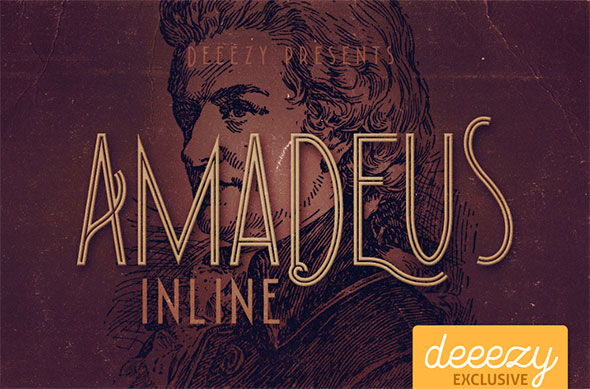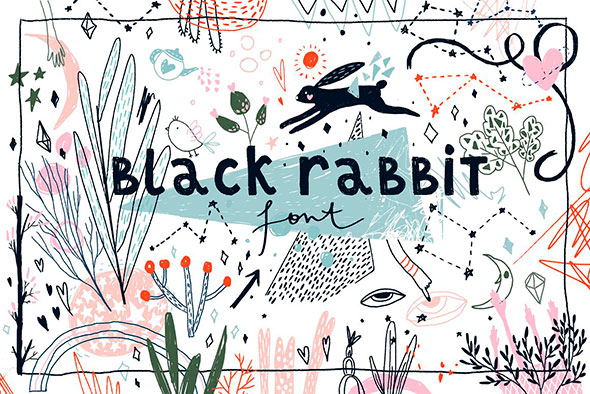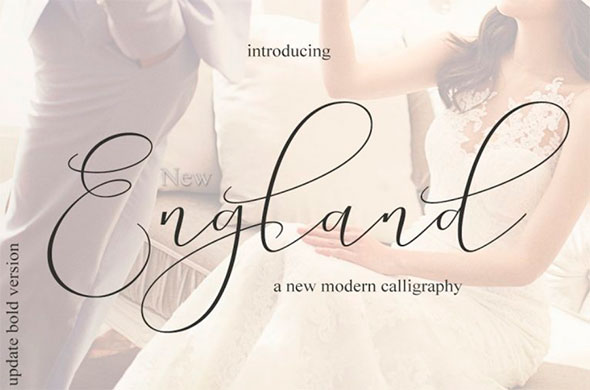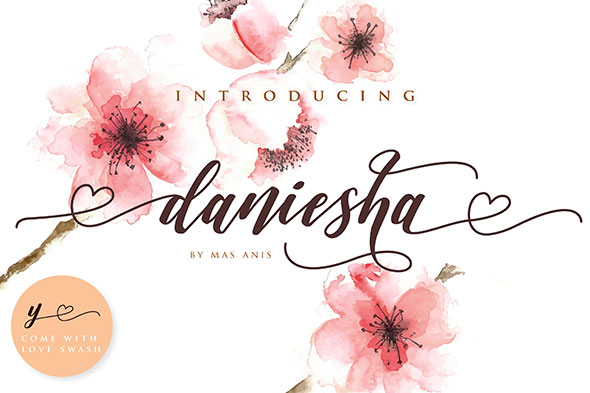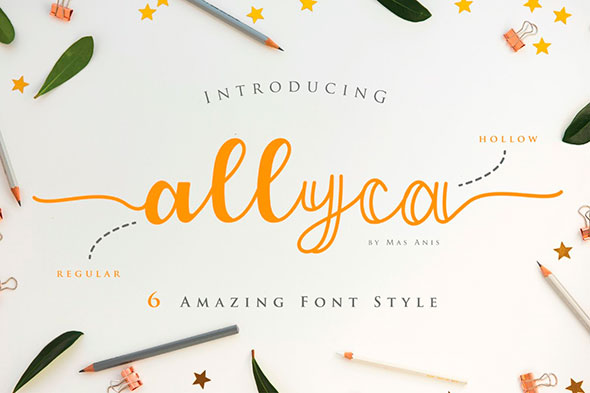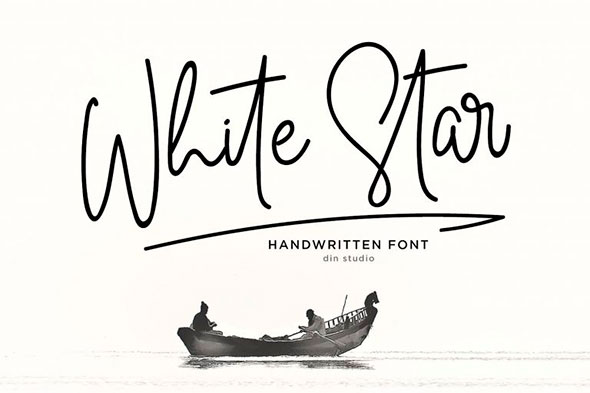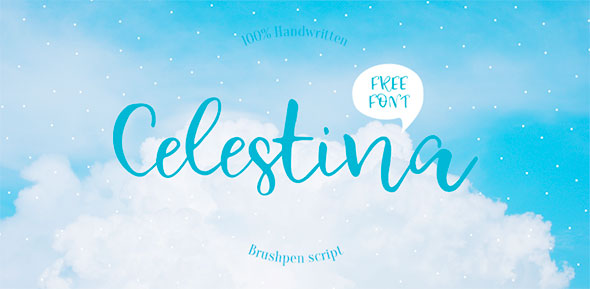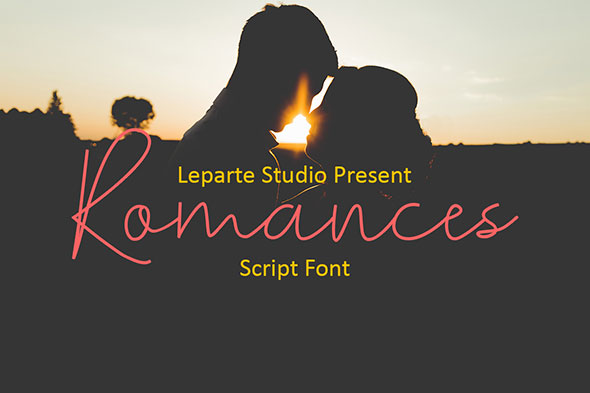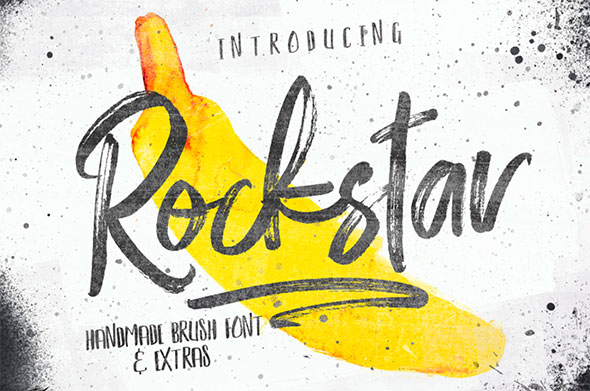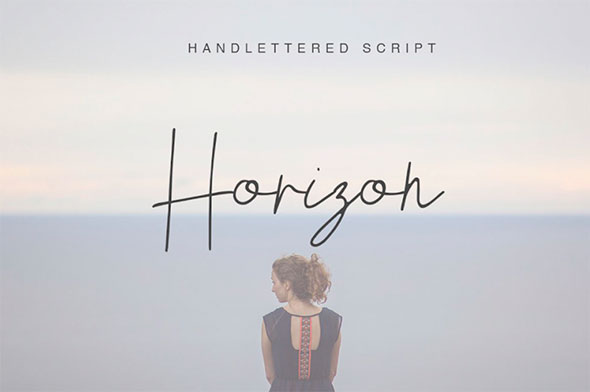
Новые шрифты для вашего дизайна
И снова подборка шрифтов для вашего дизайна. Поиск идеальных гарнитур не должен заканчиваться никогда, именно поэтому так важно держать руку на пульсе того, что происходит в этой области. В подборке доминируют декоративные шрифты, которые отлично подойдут для оформления заголовков.
Manrope (есть кириллица)
Celestina (есть кириллица)
Romances Script Font
Acrylic
Shallou
Rockstar
Horizon
Stay Writer
Ucu Aned
Amadeus
Black Rabbit
New England Script Font
Daniesha
Allyca
White Star